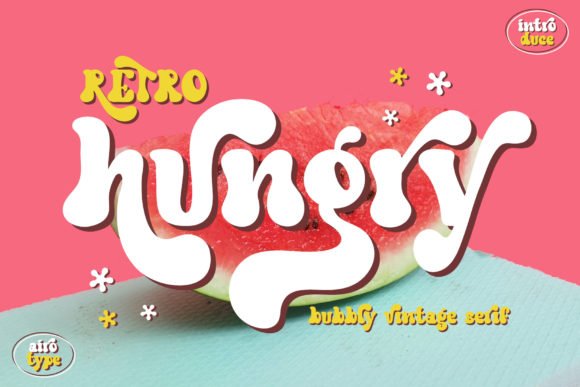
Retro Hungry Font
Retro Hungry Font – الخط المثالي لتصاميمك الكلاسيكية!
أضف لمسة من الإبداع والحنين إلى تصاميمك مع Retro Hungry Font، الخط الفريد الذي يجمع بين الطابع الكلاسيكي والطاقة العصرية. يتميز هذا الخط بأسلوبه الجريء والحروف المستوحاة من الإعلانات القديمة، مما يجعله مثالياً لتصميم الشعارات، الملصقات، عناوين المواقع، التعبئة والتغليف، والمزيد!
???? مميزات الخط:
✔️ تصميم مستوحى من الأسلوب الرجعي الكلاسيكي
✔️ مثالي للعلامات التجارية، الإعلانات، والتصاميم المبتكرة
اجعل تصاميمك تنبض بالحياة مع Retro Hungry Font وأضف إليها لمسة فريدة تأسر الأنظار! ????